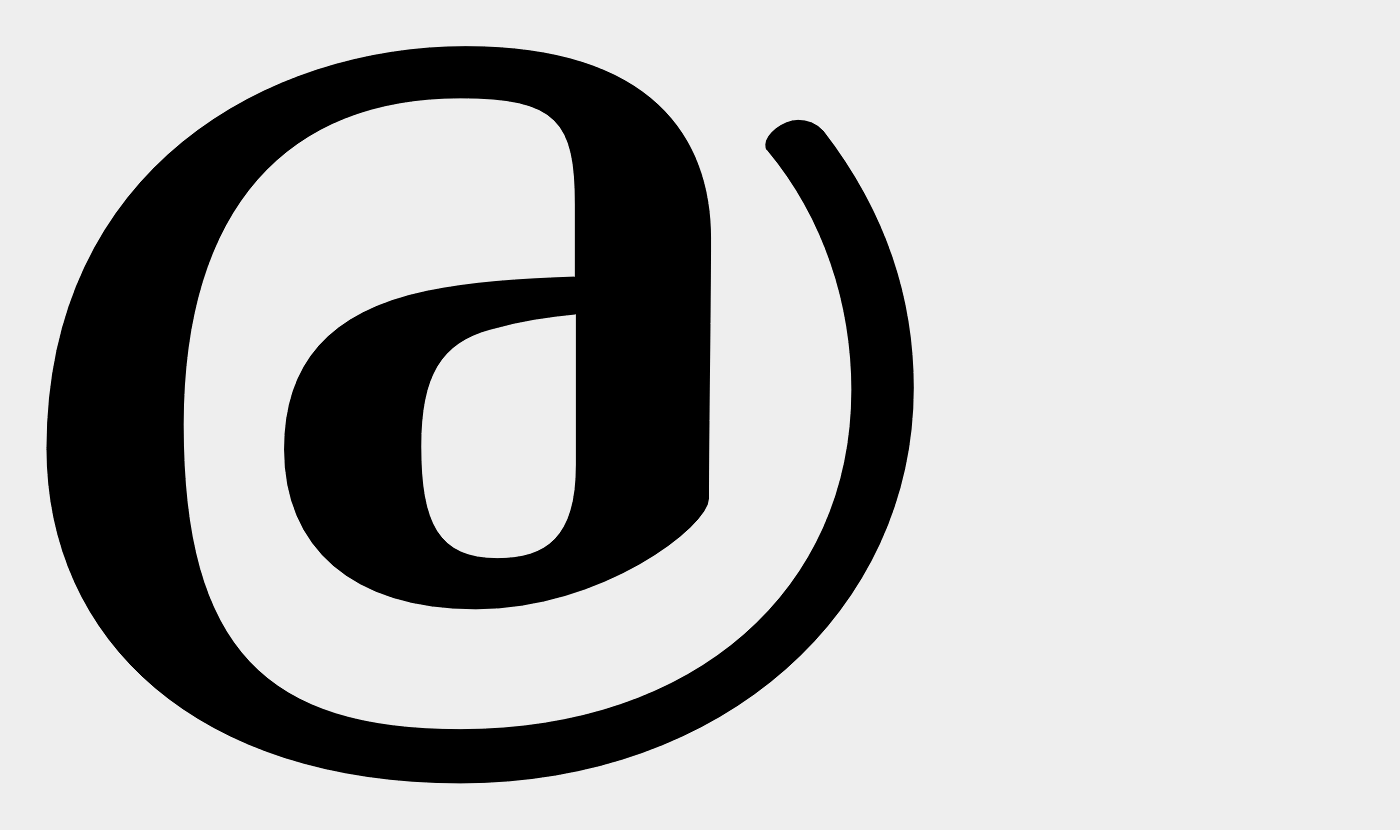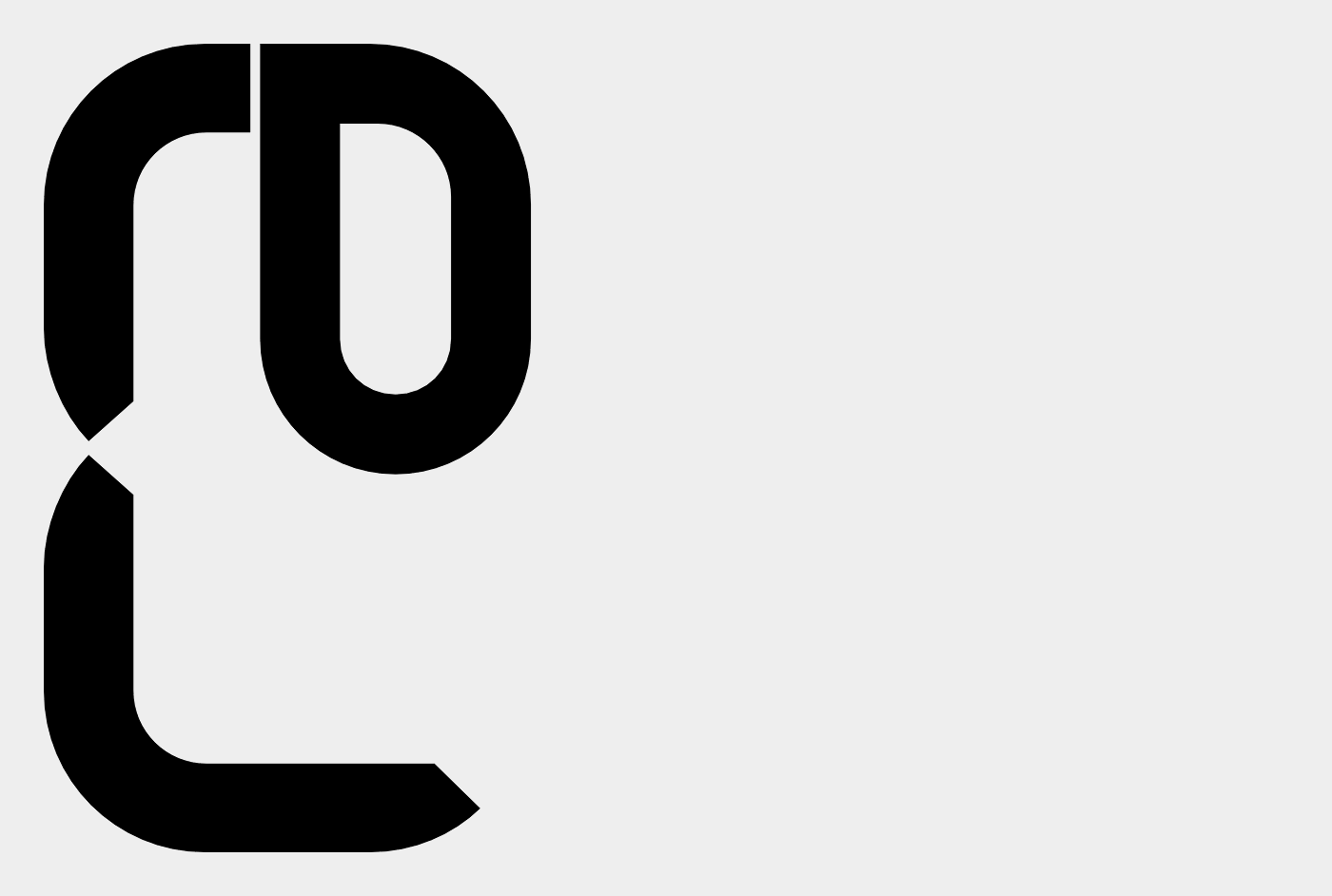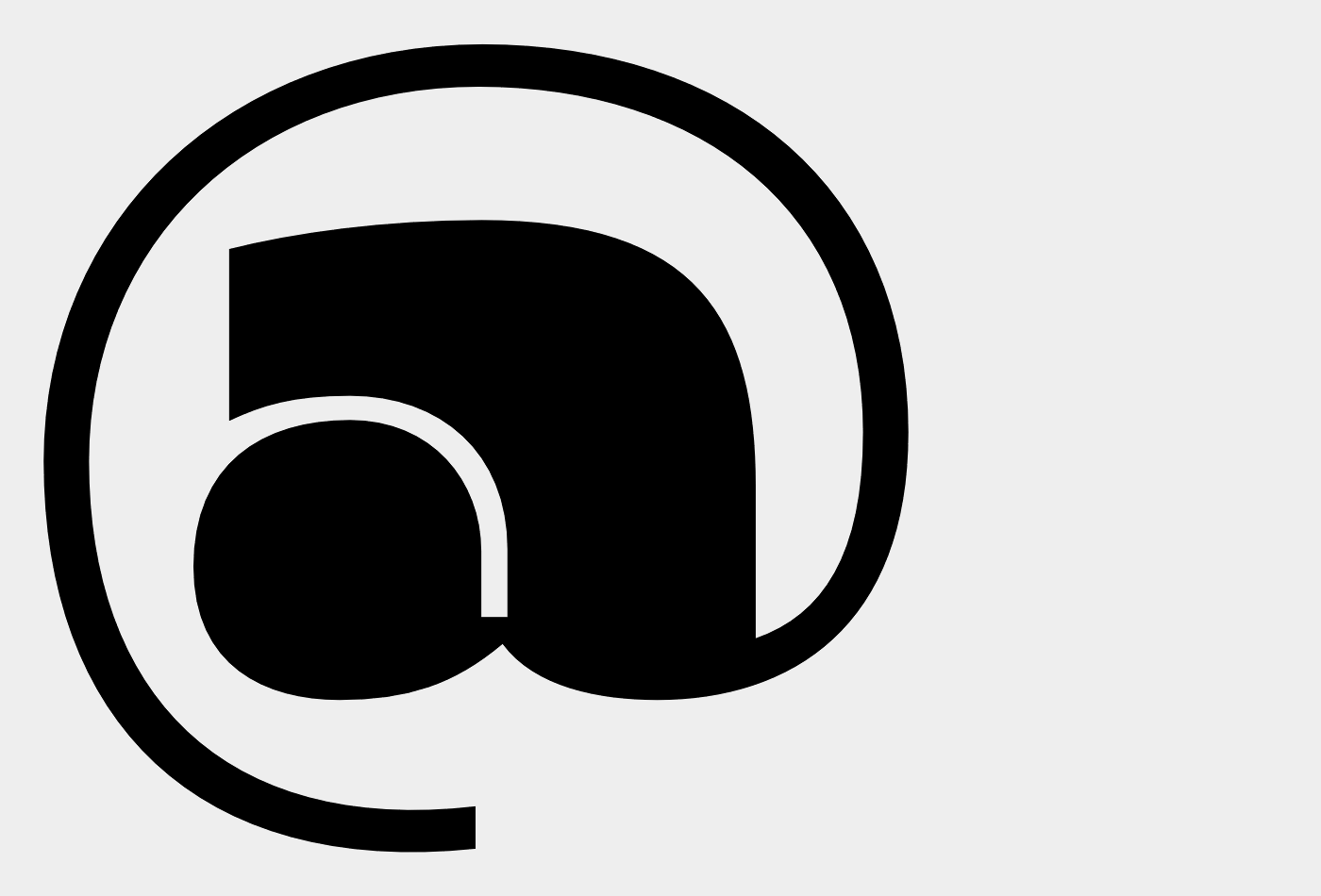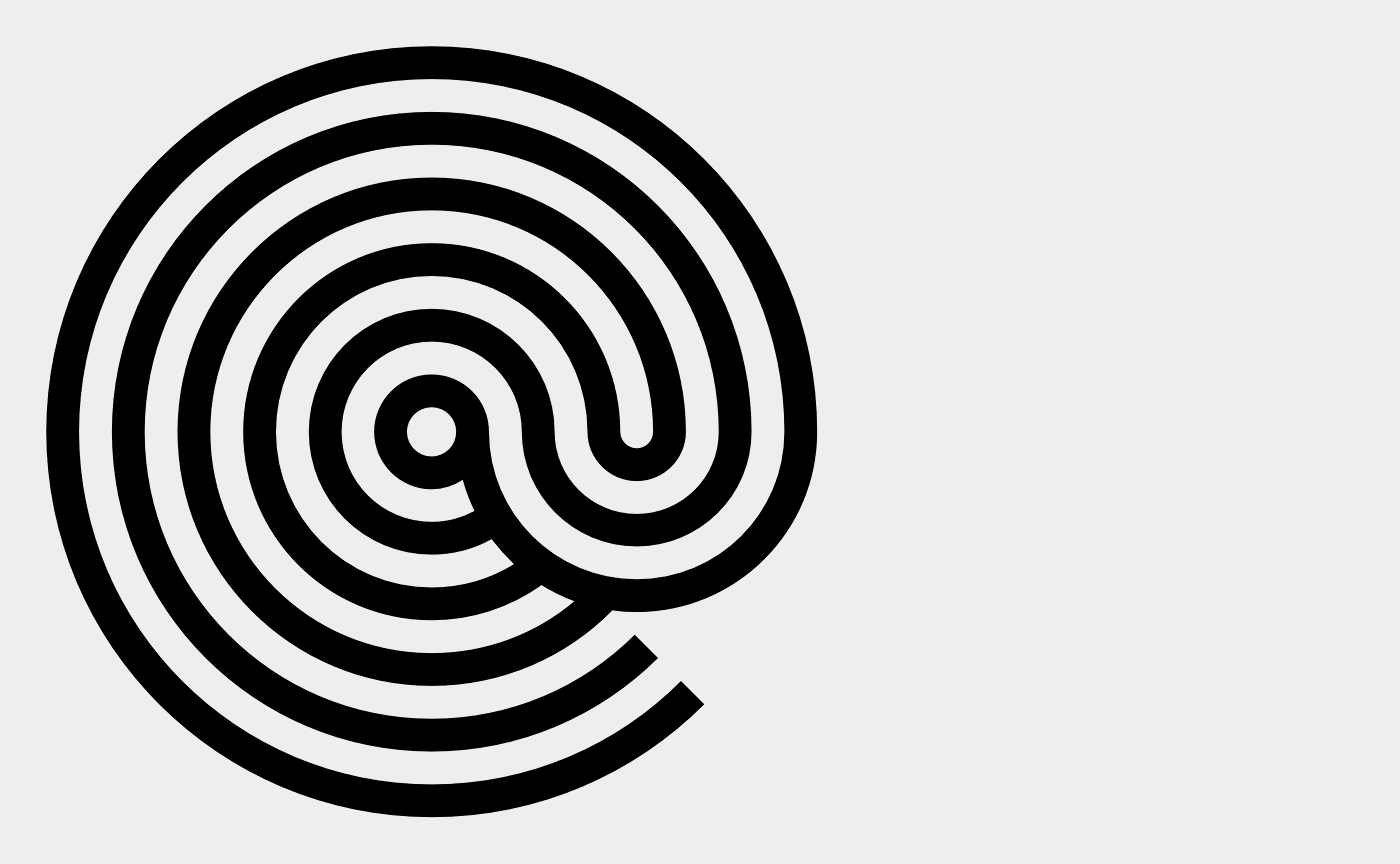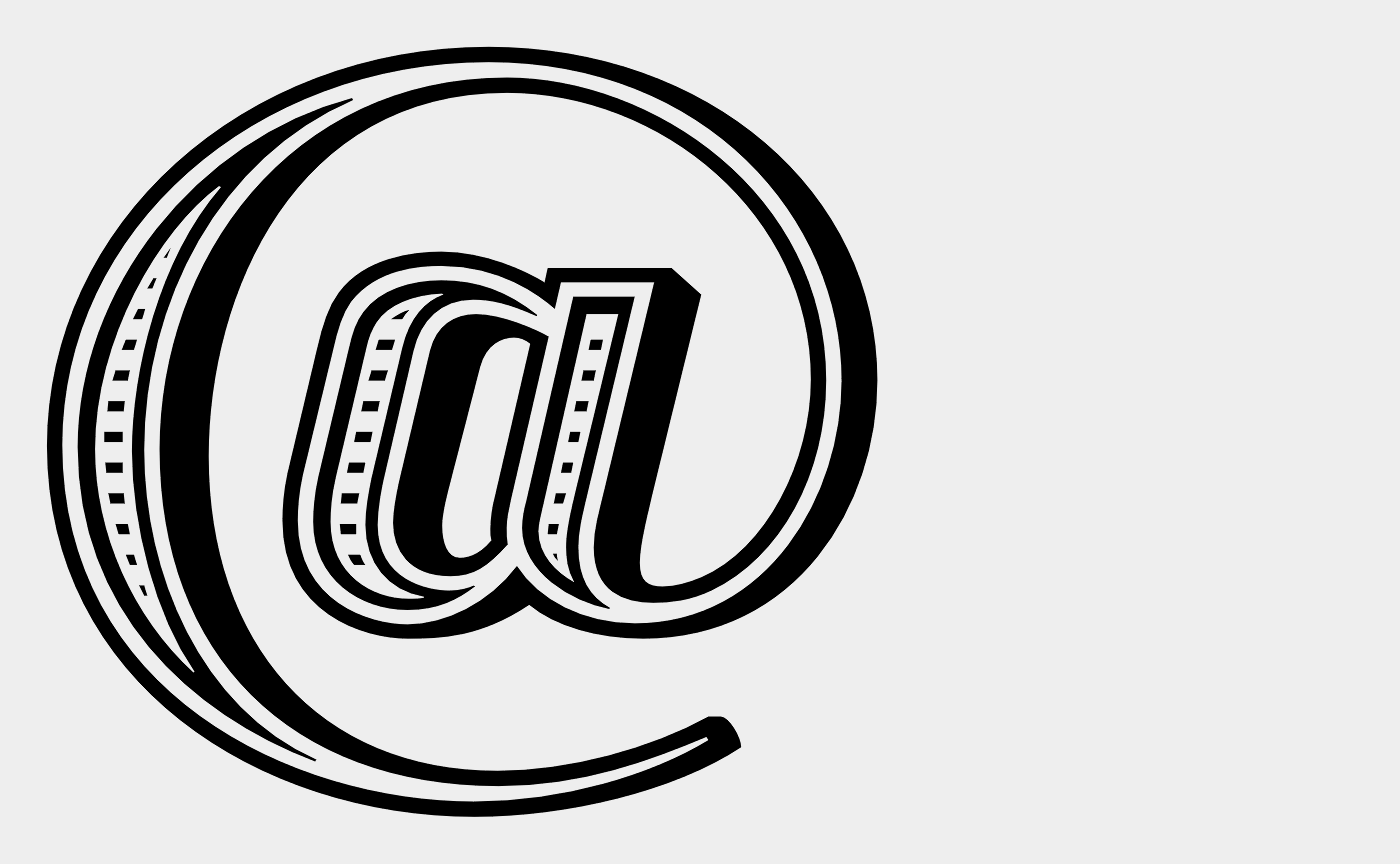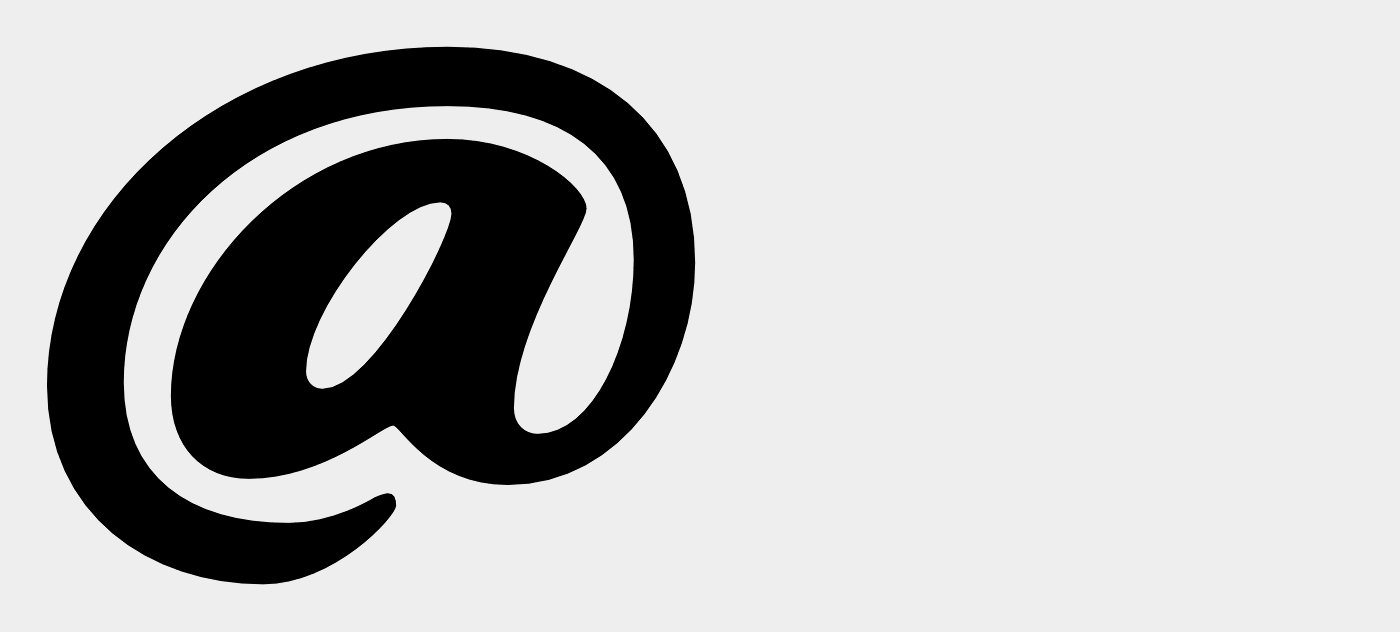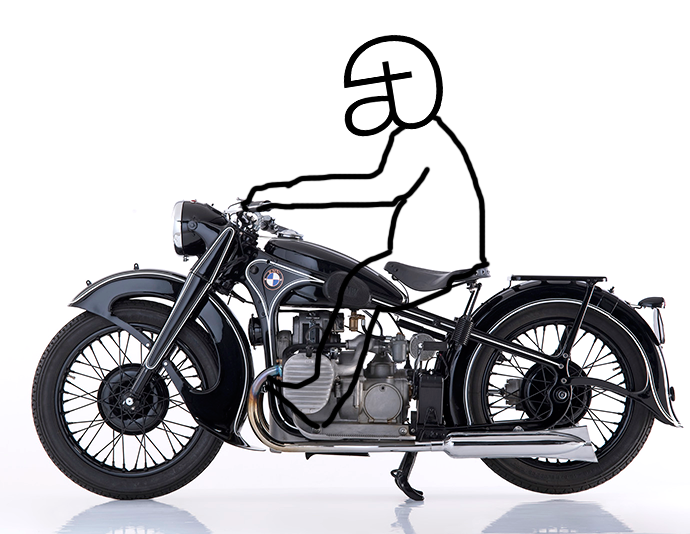
Besonders schönes @-Zeichen gesucht ...
Ja, das ist natürlich Geschmacksfrage welche Schriften man sowieso besonders liebt und letztlich sind die Variationsmöglichkeiten bei dieser Glyphe für die Schriftgestalter begrenzt. Aber trotzdem: gibt es @-Zeichen, die Ihr besonders schön oder originell findet? Ich brauche für ein Plakat ein extra großes, alleinstehendes als "Eyecatcher" und das soll möglichst besonders schön sein und dafür suche ich Anregungen und Ideen ...
Das lädt zum Spielen ein …  :hammer:
Schönen Dank für den Effra-Tip ... das hat ja auch geradezu etwas sakrales ...
Gibts noch weitere Ideen?
... das hat ja auch geradezu etwas sakrales ...
:nicken: Das war auch mein erster Gedanke. :-)
Mich würde mal das Thema interessieren. Ist ja die Frage, ob formale Extravaganz überhaupt zielführend ist oder ob man das @ auch als solches erkennen sollte.
Sollte es Dir tatsächlich um Experimente gehen (könnte man ja auch untergeordnet ergänzen), wäre evtl. auch TheSans interessant.
Sind ja tolle Sachen dabei. Ich suche natürlich eins, dass noch als solches eindeutig erkennbar ist ... und im Buchdruck gedruckt werden soll, weshalb die auf "künstlich schlechter Buchdruck" oder "pseudoabgenutzten" getrimmten Schriften für mich nicht in Frage kommen. Das kann man beim Drucken viel schöner hinbekommen.
Aber da sind jetzt schon ein paar heiße Kandidaten dabei ...
…weshalb die auf "künstlich schlechter Buchdruck" oder "pseudoabgenutzten" getrimmten Schriften für mich nicht in Frage kommen. Das kann man beim Drucken viel schöner hinbekommen ...
deshalb ja auch:
Wie wär’s mal mit selber machen – D.I.Y. ;-)
Die Beispiele sollten Dich nur inspirieren.
Ja, so war ja auch die Frage gemeint. Ich wollte ja nur erklären, warum ich bei diesen Schriften nicht ein "gefällt mir" gehakt habe - war keinesfalls als Kritik gemeint. :nicken:  :nicken: Komplett selber machen kann ichs ja nicht, da ich keine Schriften gestalte ... ich muss halt erst ne Schrift haben, ehe ich setze und drucke ...